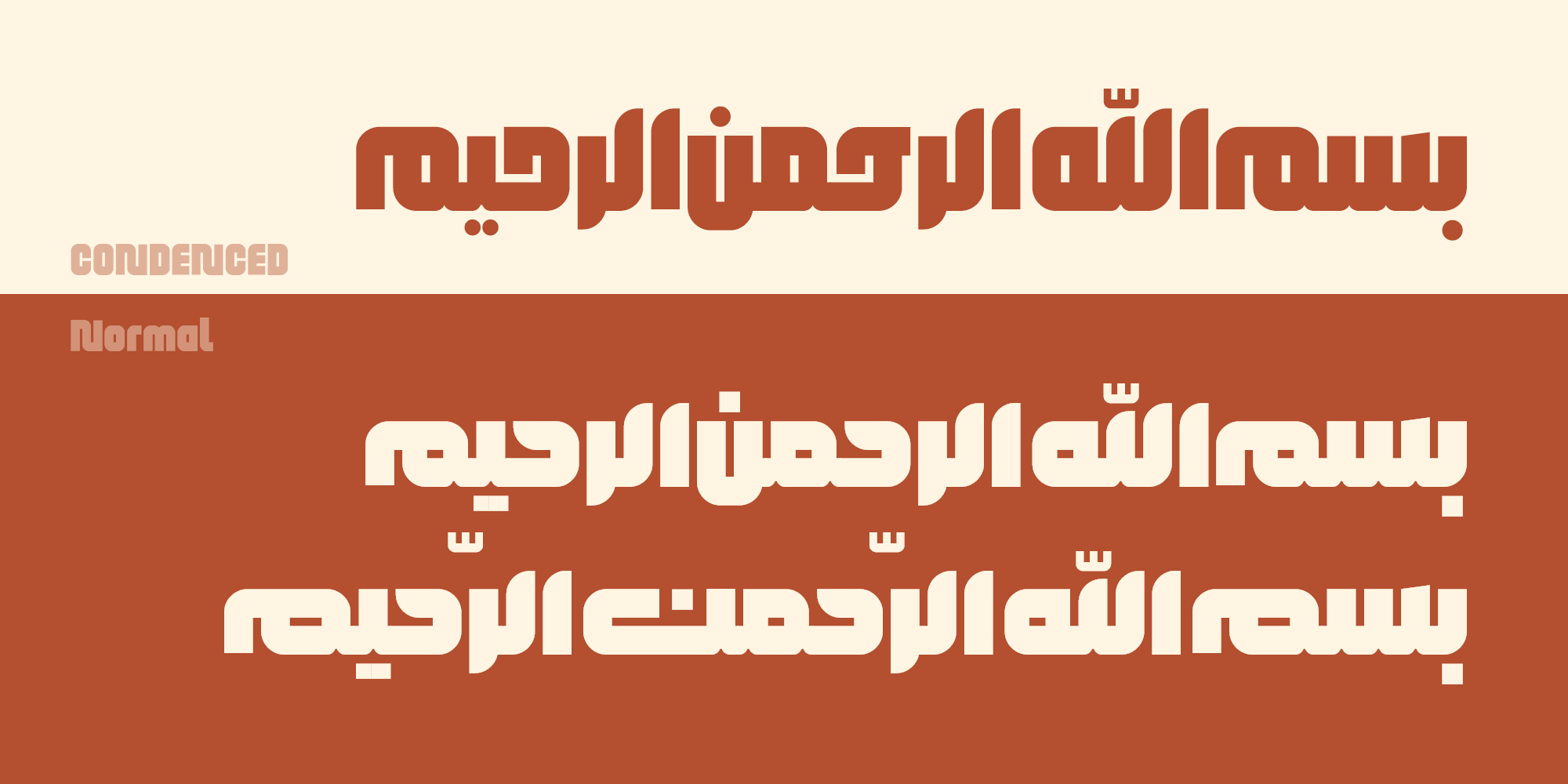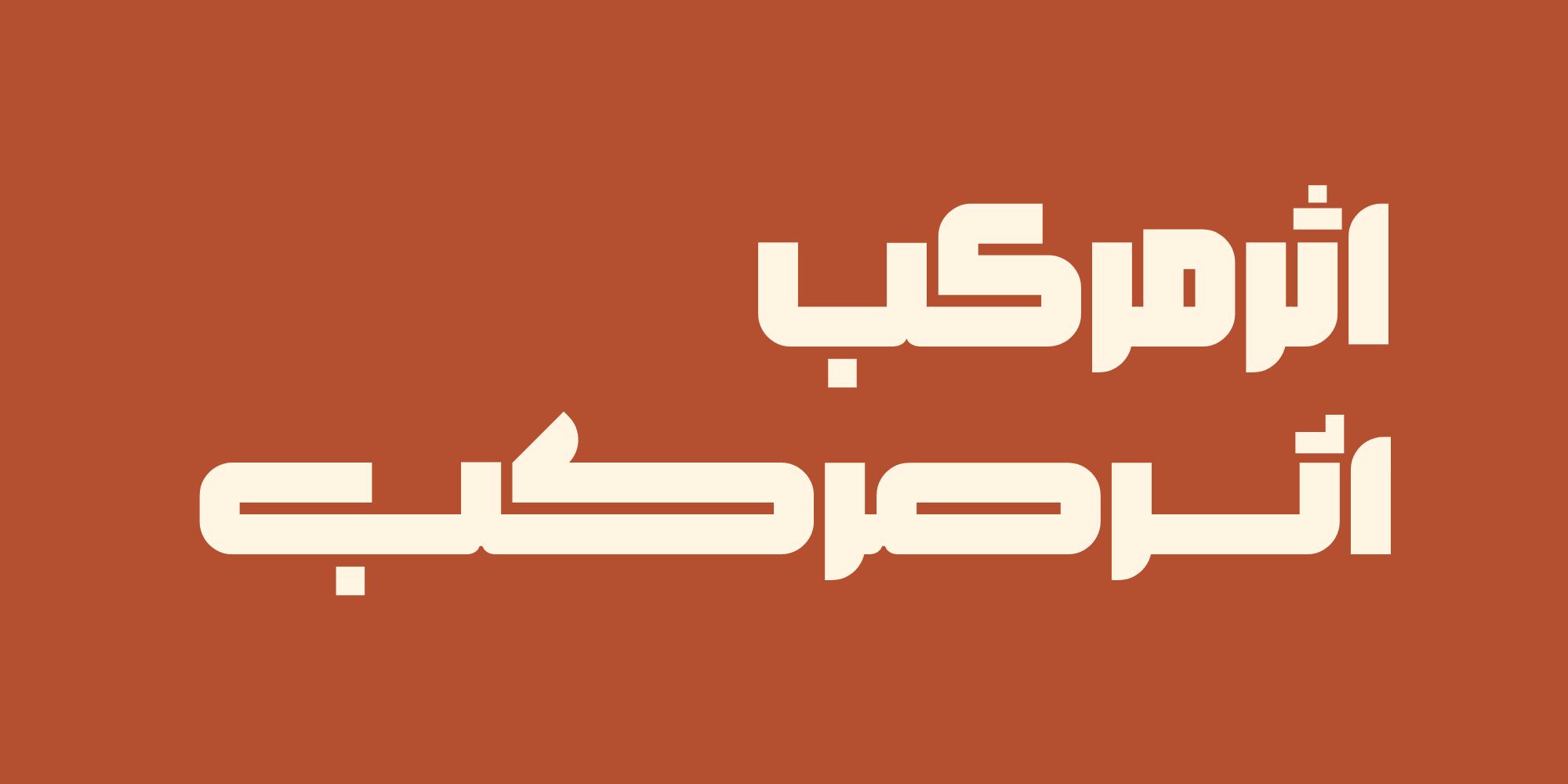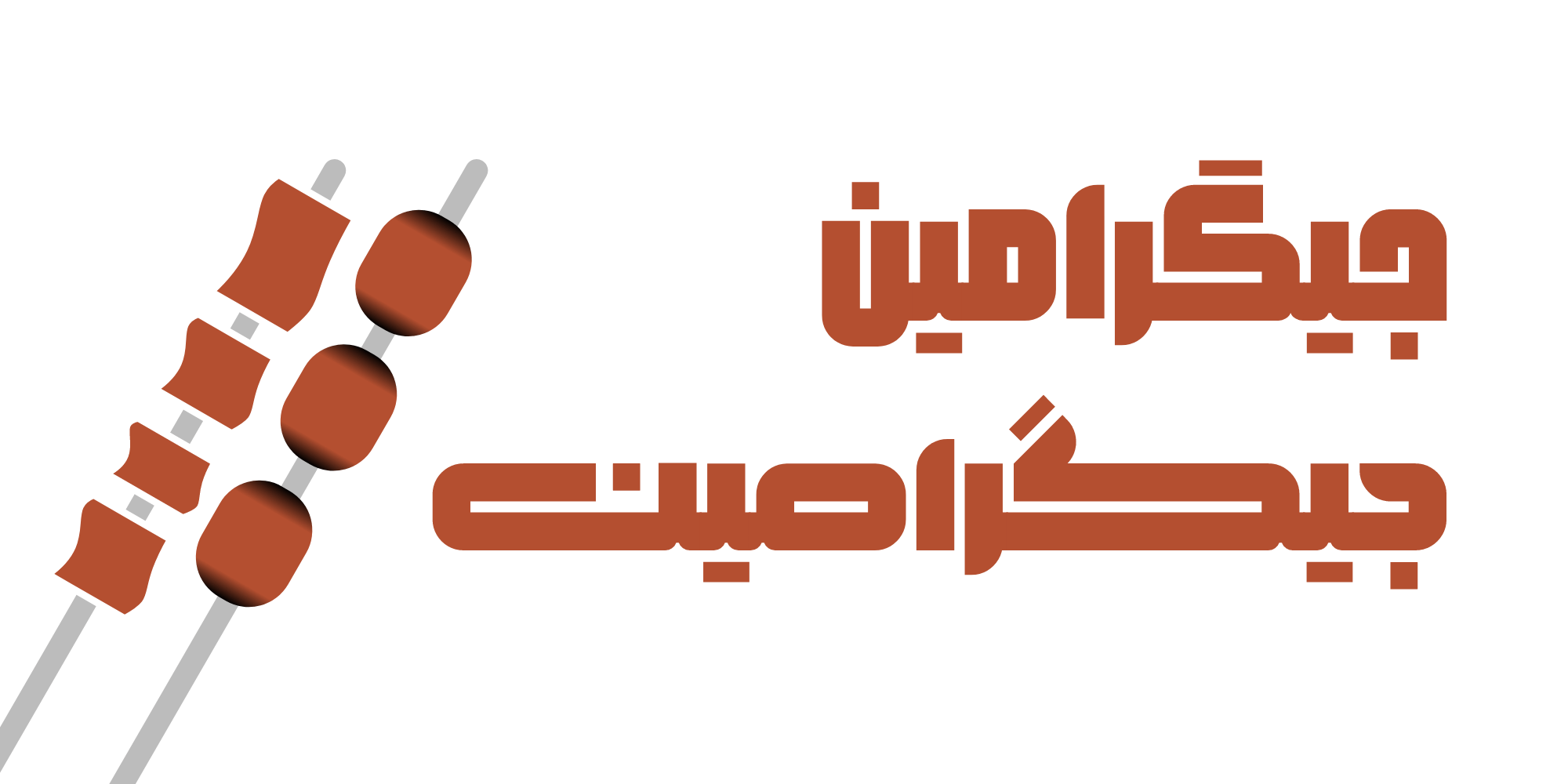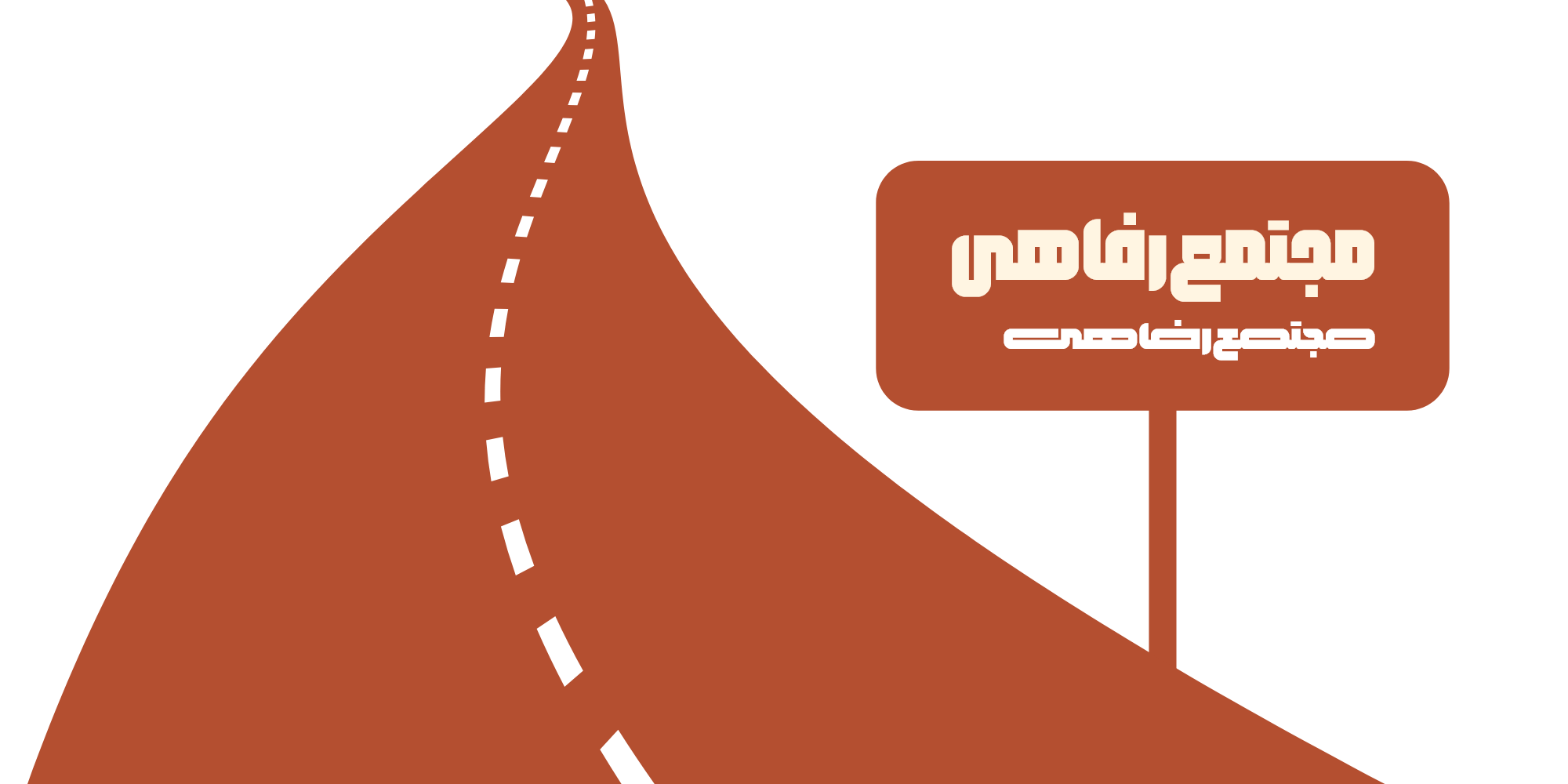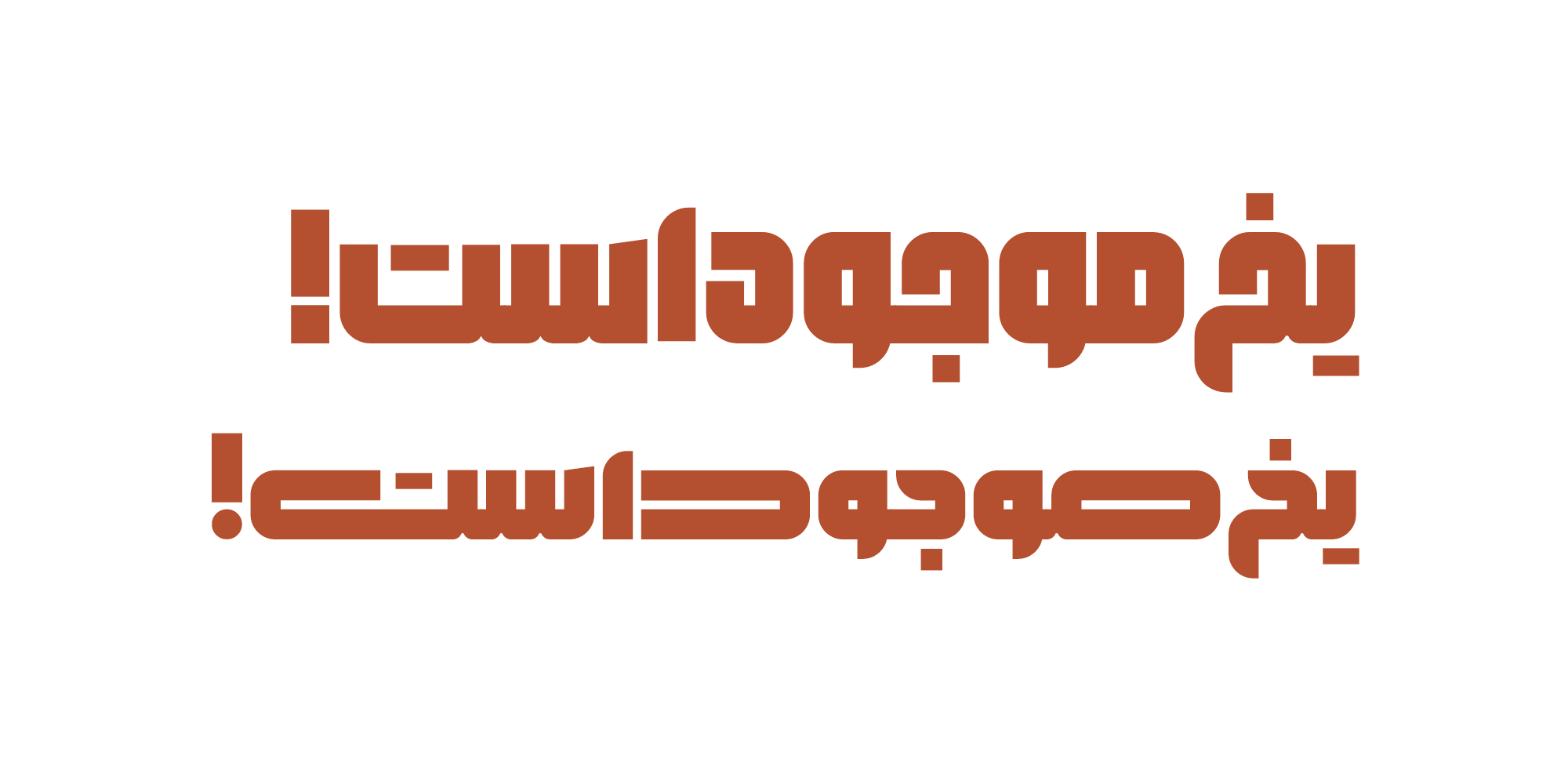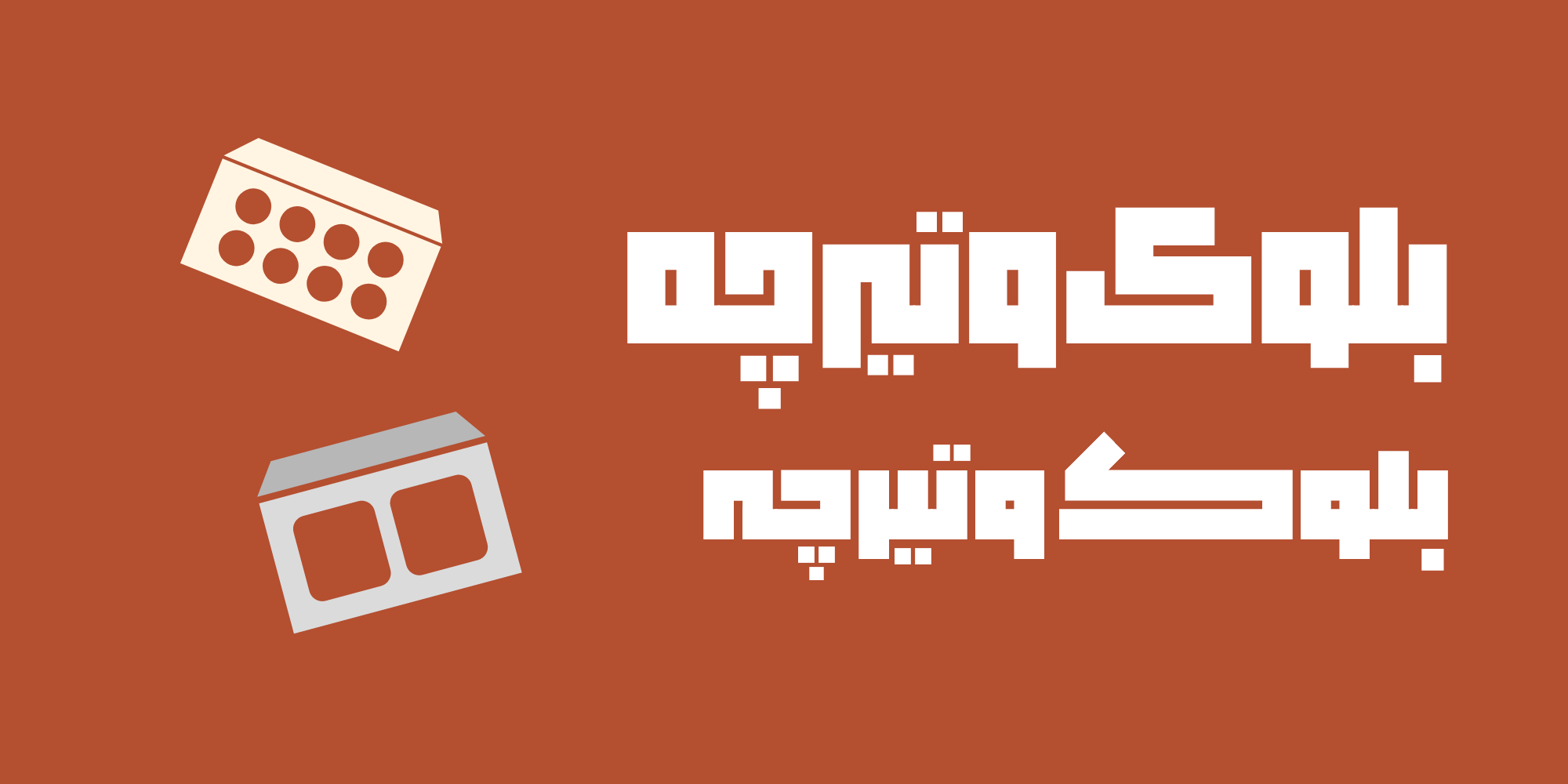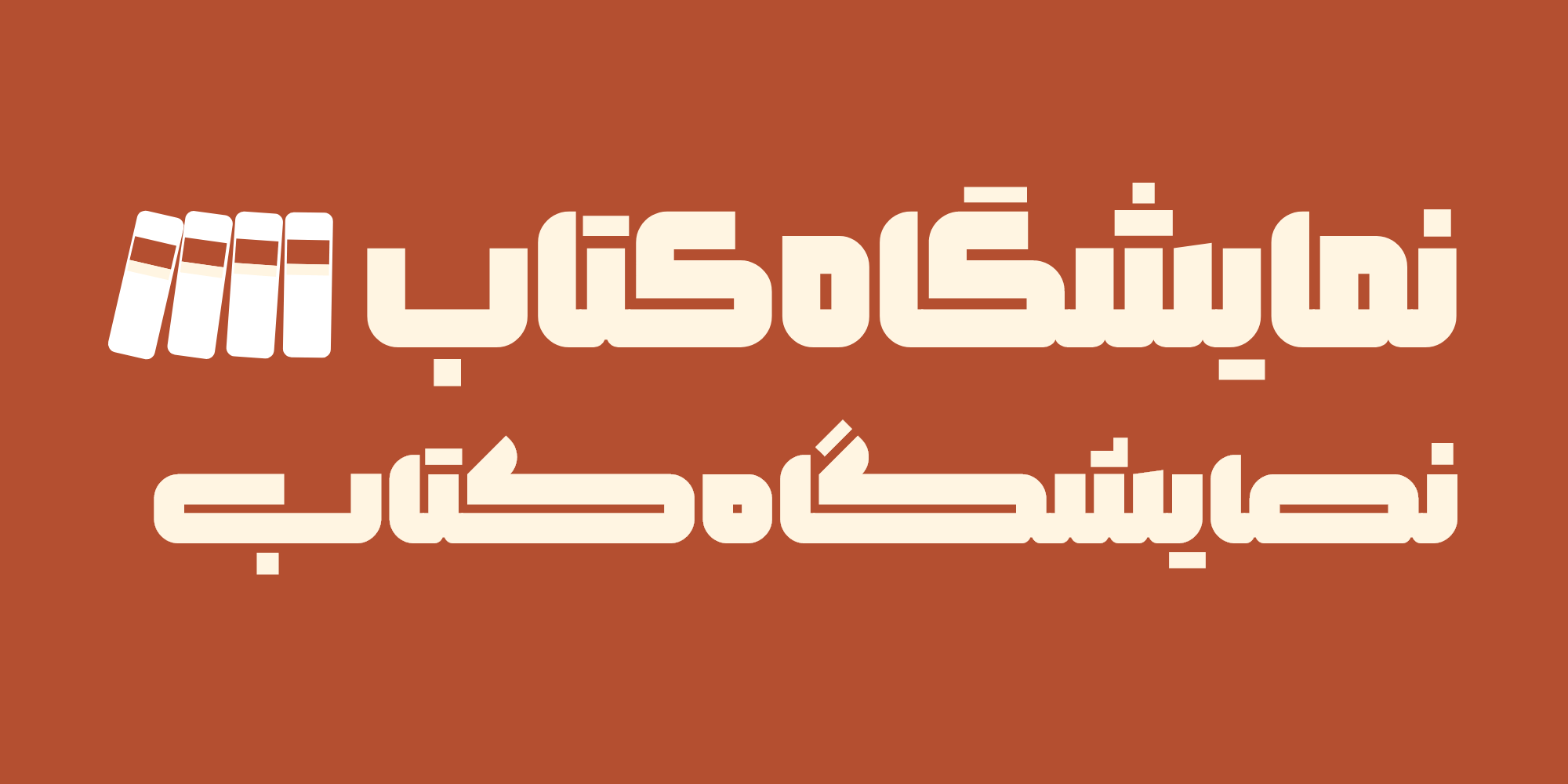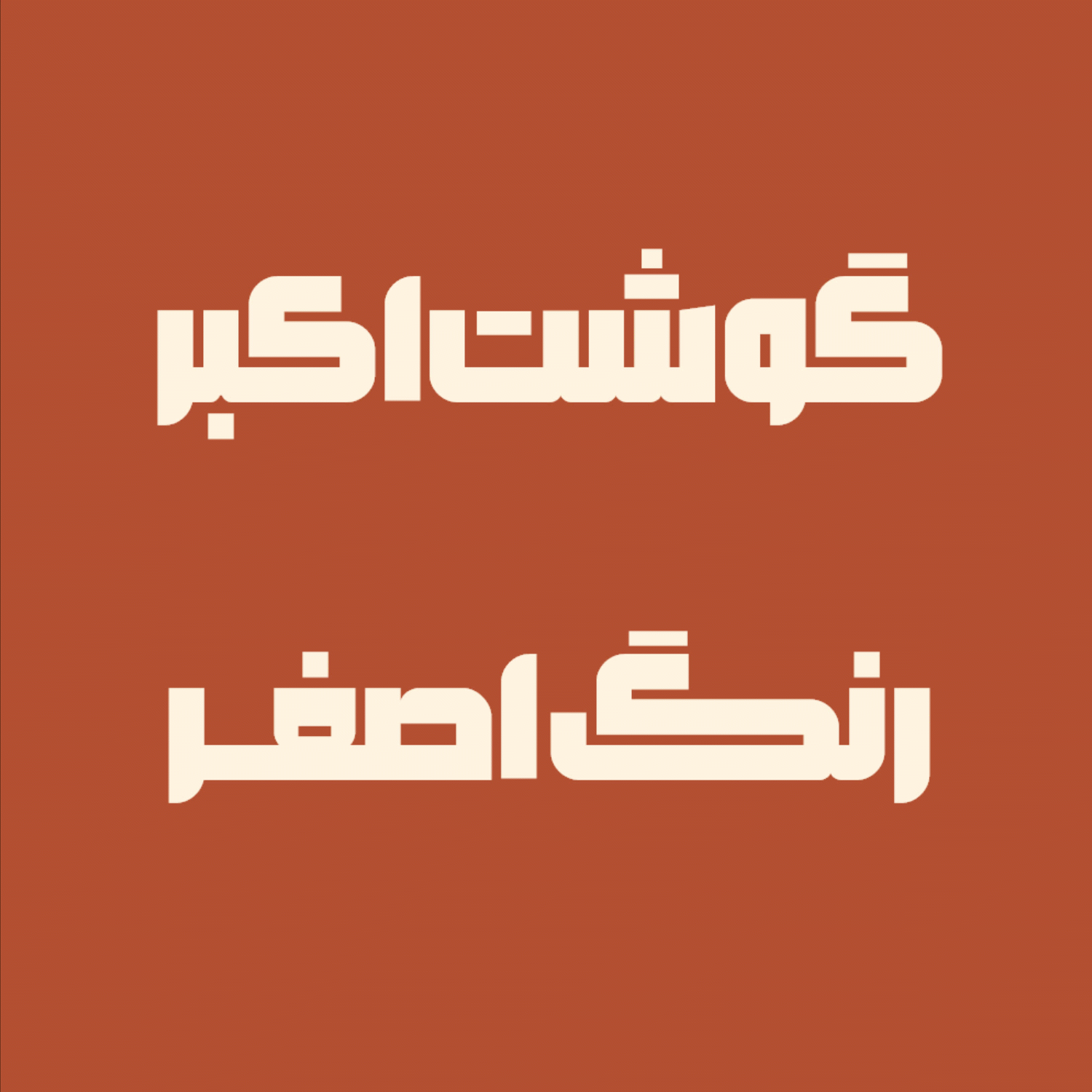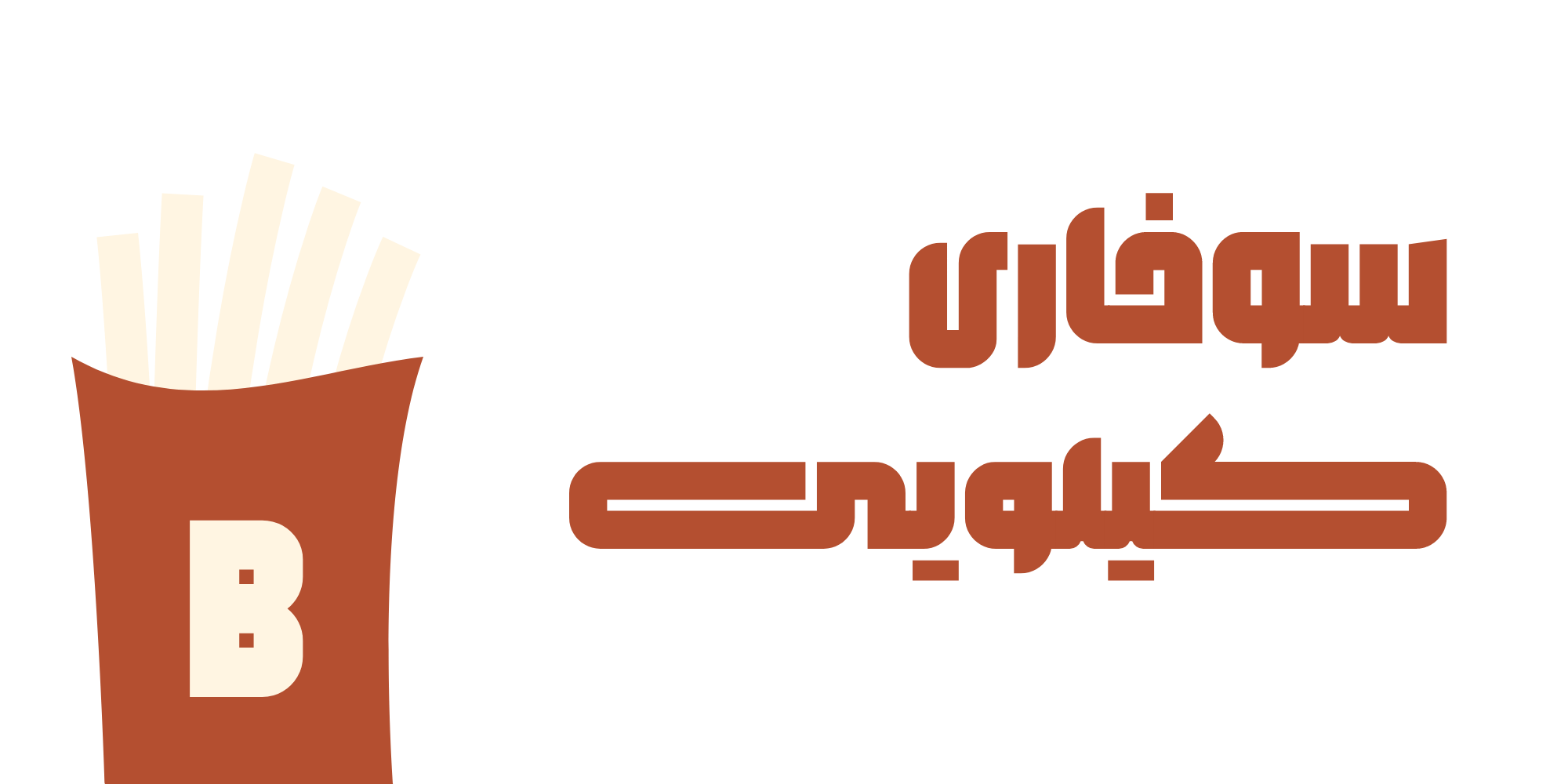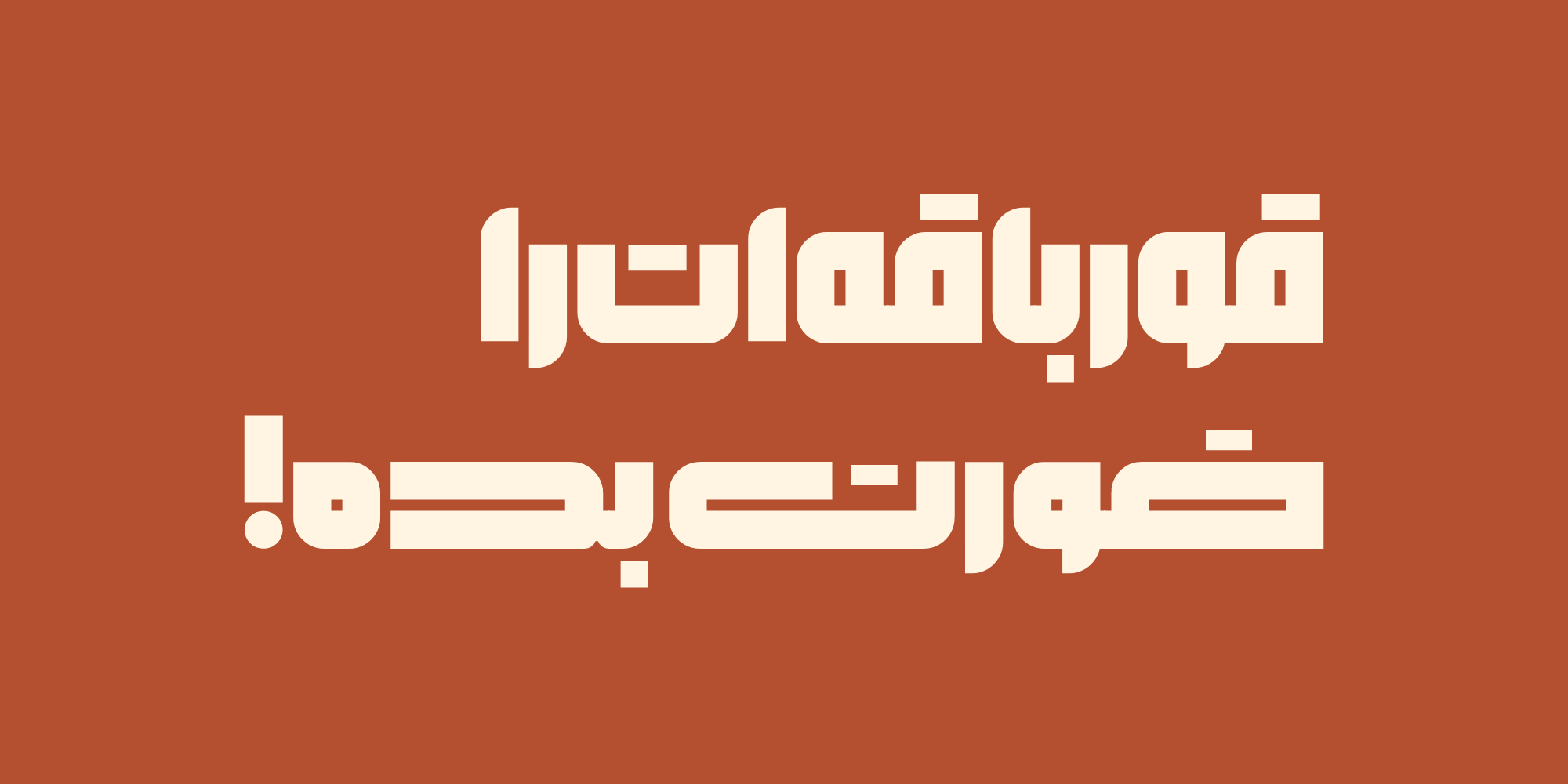
استایلهای فونت بلوک
فونت بلوک بطور کلی در دو استایل فرمی و شخصیتی پیاده سازی شده است: استایل سخت یا Sharp که دقیق، منظم، خشک، جدی و کمی وسواسی است و استایل نرم یا Round که شخصیتی نسبتا مهربان، صمیمی و دوستانهتر دارد، درک مناسبتری از احساسات دارد و با مخاطب با قولِ لیّنتری صحبت میکند و به قول معروف سعی میکند با گفتگو مسئله را حل کند!
درمورد هردو استایل امکان تغییر فرم حروف و نوع نقطهها، میزان نرمی و قوس گوشهها و همچنین استفاده از ترکیبات جایگزین و کشیدگیها بصورت مجزا فراهم است.
در نسخه دوم فونت بلوک علاوه بر این دو استایل در سبک عادی یک سبک نسبتا فشرده یا Condensed به بسته اضافه شده که در این سبک برخی حروف بجای امتداد در محور افق، با افزایش یک ردیف ارتفاع بیشتر امکان فشرده تر شدن افقی نوشتار را فراهم میکنند و این موضوع در مجموع میتواند دست دیزاینر را در چیدمان هرچه بهتر بازتر کند…
سبک کاندِنسد (فشرده) سبکی رایج در بین تایپفیسهای لاتین بوده که به تازگی بطور پخته تری وارد فضای نوشتار فارسی نیز شده است…
برای ایجاد تنوع بیشتر از قابلیتهای خط بنایی بیشتر استفاده کردیم و در نتیجه تعدادی مفردات و ترکیبات جایگزین به حروف اضافه شده که به کاربر امکان خلاقیت و نوآوری بیشتری را ارائه میدهد.
همچنین برای انعطاف بیشتر و تناسب بین فضاها امکان ایجاد کشیدگی های نوین به حروف فونت بلوک اضافه شده که به کاربر امکان میدهد تا بجای دفورم کردن حروف و یا ایجاد فضای خالی نامتناسب خود حروف را تغییر دهد.
چراغ فونت بلوک از آنجایی در ذهن من روشن شد که خلاء و کمبودی را در فضاهایی حس کردم که عناوین کوتاه میبایست برجسته و تاثیرگذار ظاهر شوند اما به دلیل عدم پیشرفت تایپ فارسی در یک بازهی محدود و تمرکز بیشتر دیزاینرها بر تایپفیسهای متن، به این فضا توجه کمتری شده و تایپفیسی که مناسب این فضا باشد و از فرم نوآورانهای برخوردار باشد کمتر یافت میشد.
تعداد محدودی از تایپفیسهای موجود هستند که هنوز هم علیرغم تحول تایپ فارسی جزو انتخاب های اول و اصلی طراحان گرافیک و تابلوسازان هستند.
تایپفیس هایی مانند تیتر، یکان، زر، نازنین، میترا و غیره که عمدتا تاثیر زیادی از خط نسخ گرفته اند در زمان خودشان شاهکار بودند اما استفادهی مکرر از آنها و راکد ماندن این فضا برای مدتی طولانی از جذابیت های فرمی این تایپفیسها به شدت کاسته.
به همین علت سعی کردم تا حد قابل توجهی از خط پر استفادهی نسخ فاصله بگیرم و دربین رسم الخطوط فارسی/عربی خط بنایی یا معقلی را برای این فضا مناسب تر دیدم به این علت که این خط برخلاف خیلی از خطوط دیگر که با خوشنویسی بوجود آمده اند با کنارهم قرارگرفتن بلوکهای آجری پدید آمده و همین موضوع تناسب بیشتری را برای فضاهایی مثل تابلو یا کتاب که ابعادی مستطیل شکل و هندسی دارند فراهم میکند.
البته خط بنایی به خودی خود خطی خشک و بشدت سخت خوان است و معمولا استفاده از این خط در کتیبهها و تابلوها بیشتر متمرکز بر تناسب فضاهای مثبت و منفی بوده تا خوانایی.
اما داشتن کرسی متحرک، انعطاف و تنوع بسیار بالا در حروف، تناسبات به شدت دقیق و هماهنگ، سواد و بیاض به شدت تکامل یافته و نزدیکی فرم برخی از حروف به خطوط دیگر مزیتهای خط بنایی بودند که مرا جذب کردند.
لذا تصمیم گرفتم با افزودن ویژگیهایی مانند قوسها، خطوط مورب، فاق، زاویهی قلم و ملاحضاتی درچشمها از خطوط دیگر از جمله نسخ، ثلث، نستعلیق و کوفی کمی این خط را برای جامعهی عمومی قابل پذیرش کنم و مردم بیشتری بتوانند از مزایای این خط مغفول بهره ببرند، نتیجهی این دیدگاه و البته راهنماییهای اساتید خوبم دامون خانجانزاده، مسلم ابراهیمی و امین عابدی عزیز که هم در مسیر توسعهی فنی و هم فرمی فونت بلوک همراه من بود بسیار تاثیرگذار بود.
یکی از موضوعاتی که در بروزرسانی فونت بلوک و بافراگیری مطالب جدیدی در کلاس استاد خانجانزاده و دوست عزیزم رضا مرادی سعی در اعمال و اجرای آن داشتم اصلاحات اوپتیکال بود که تا حد امکان از دچار شدن مخاطب به خطا یا توهم بصری یا Optical Illusion جلوگیری کند، اگرچه این موضوع کمتر درمورد فونتی مثل بلوک ممکن است رخ بدهد اما موارد محدودی بودند که با بررسی و اصلاح آنها تاثیرات زیادی را در تناسبات و خوانایی مشاهده کردم.